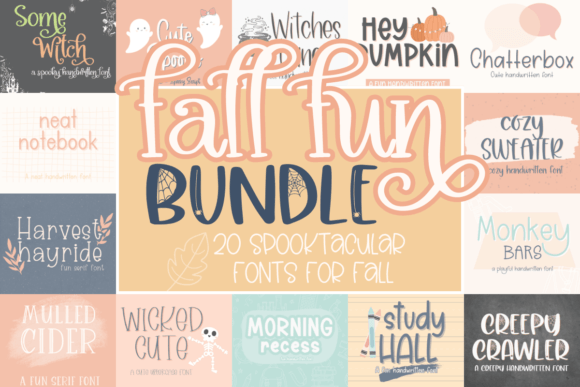
Fall Fun Font Bundle
Die richtigen Designelemente zu finden, kann eine Herausforderung sein, aber Fall Fun Font Bundle bietet eine außergewöhnliche Sammlung, die Ihre Arbeit sofort aufwertet.
Egal, ob Sie POD-Produkte (Print on Demand), Hochzeitseinladungen oder Social-Media-Grafiken erstellen, Fall Fun Font Bundle ist die ideale Wahl.